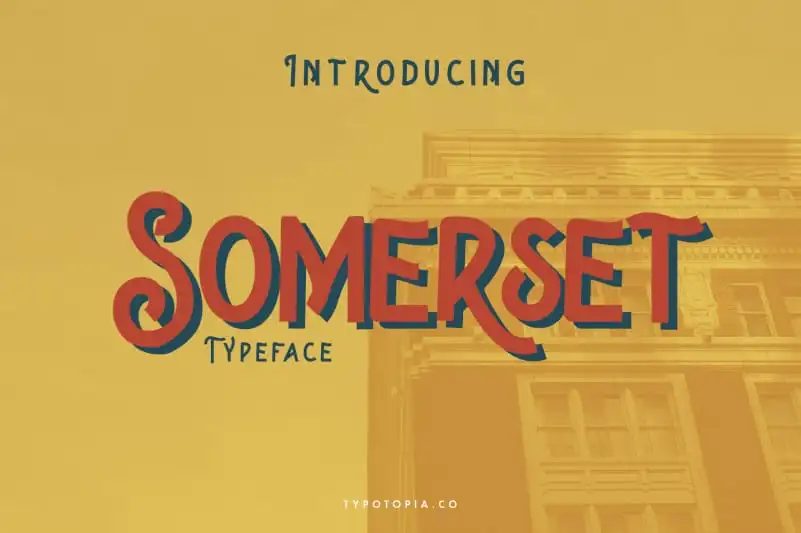
Somerset Display Font – Download Grátis
A Somerset Display Font é uma seleção cuidadosa de estilos vintage modernos, perfeita para quem busca dar uma personalidade única a suas criações digitais. Com uma variedade de quatro tipografias diferentes, esta família de fontes oferece um ar de elegância e sofisticação ao seu trabalho. Ideal tanto para a digital lettering quanto para logotipos, camisetas, impressões, cartões de negócio e materiais de marca, bem como ideais para criações de citações, fotografia natural e outras aplicações gráficas criativas. Este estilo elegante é resultado do trabalho meticuloso dos artistas, inspirados por estilos vintage e modernos. A Somerset Display Font é uma seleção perfeita para aqueles que desejam dar um toque único à sua arte digital, tornando-a ainda mais intrigante e atraente. Com suas linhas arquitetônicas e detalhes cuidadosamente elaborados, esta fonte vem com tudo o que precisa para fazer seu design realmente brilhar em qualquer aplicação.